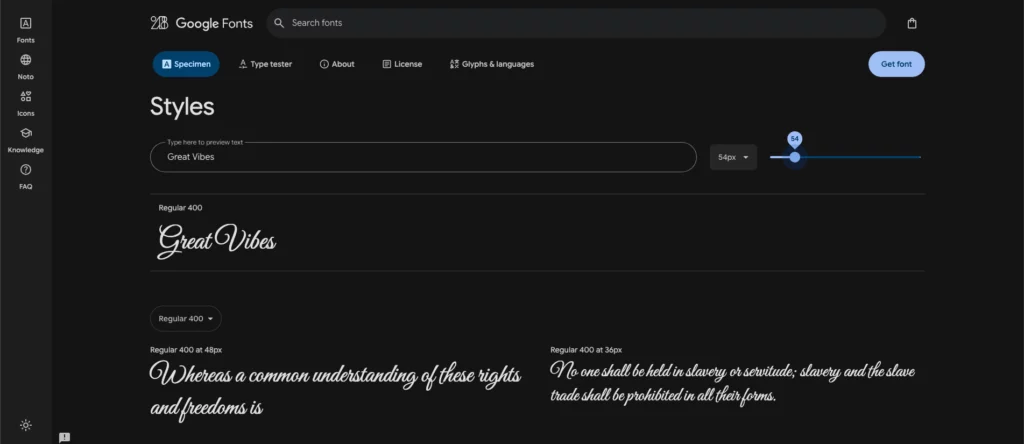
การเลือกฟอนต์ที่เหมาะสมเปรียบเสมือนการเลือกเสื้อผ้าให้กับข้อความของคุณ ในโลกของการออกแบบดิจิทัลที่มีการแข่งขันสูง ฟอนต์มีความสำคัญมากกว่าที่คุณคิด มันไม่เพียงแต่ช่วยให้ข้อความอ่านง่ายขึ้น แต่ยังช่วยสร้างความประทับใจแรกและส่งเสริมตัวตนของแบรนด์ คุณเคยสังเกตไหมว่า แบรนด์ชั้นนำระดับโลกต่างใช้ฟอนต์เฉพาะที่ทำให้เรานึกถึงพวกเขาทันทีที่เห็น
บทความนี้จะพาคุณไปรู้จักกับฟอนต์ภาษาอังกฤษที่สวยงาม 20 แบบ ซึ่งคุณสามารถดาวน์โหลดและใช้ได้ฟรีในปี 2025 พร้อมคำแนะนำเกี่ยวกับวิธีเลือกฟอนต์ให้เหมาะกับงานแต่ละประเภท
ทำไมฟอนต์ถึงสำคัญกับงานดีไซน์
ฟอนต์ คือชุดของตัวอักษรที่มีรูปแบบเฉพาะ น้ำหนัก และลักษณะพิเศษที่ออกแบบมาเพื่อใช้งานร่วมกัน ฟอนต์ภาษาอังกฤษที่มีคุณภาพสูงจะมีความสม่ำเสมอในการออกแบบ อ่านง่าย และมีความยืดหยุ่นในการใช้งานหลากหลายรูปแบบ และองค์ประกอบสำคัญของการออกแบบเพราะมีอิทธิพลโดยตรงต่อความรู้สึกของผู้ชม มันสามารถสร้างความน่าเชื่อถือ ความเป็นมืออาชีพ หรือความคิดสร้างสรรค์ได้โดยไม่ต้องใช้คำพูดใด ๆ
ความแตกต่างของฟอนต์ภาษาอังกฤษในแต่ละสไตล์
ฟอนต์ภาษาอังกฤษมีหลายประเภท แต่ละประเภทมีความโดดเด่นแตกต่างกัน
Serif – มีเส้นตกแต่งเล็ก ๆ ที่ปลายของแต่ละตัวอักษร ให้ความรู้สึกเป็นทางการและคลาสสิก เหมาะกับเนื้อหาที่ต้องการความน่าเชื่อถือ
Sans-serif – ไม่มีเส้นตกแต่งที่ปลายตัวอักษร ดูทันสมัยและเรียบง่าย เหมาะกับการอ่านบนหน้าจอดิจิทัล
Display – ออกแบบมาเพื่อดึงดูดความสนใจ มักใช้กับหัวข้อขนาดใหญ่หรือโลโก้
Script – เลียนแบบลายมือเขียน ให้ความรู้สึกเป็นส่วนตัวและมีศิลปะ
Monospace – ตัวอักษรแต่ละตัวมีความกว้างเท่ากัน นิยมใช้ในการเขียนโค้ดหรืองานที่ต้องการความแม่นยำ
บทบาทของฟอนต์ในการสื่อสารแบรนด์และอารมณ์
ฟอนต์เป็นเสมือนน้ำเสียงของแบรนด์ในรูปแบบที่มองเห็นได้ เมื่อคุณเลือกฟอนต์ที่เหมาะสม มันจะช่วยถ่ายทอดบุคลิกของแบรนด์ได้อย่างมีประสิทธิภาพ
ตัวอย่างเช่น ฟอนต์เรียบง่ายแบบ Sans-serif อาจสื่อถึงความทันสมัยและความเป็นมืออาชีพ ขณะที่ฟอนต์แบบ Script อาจให้ความรู้สึกถึงความเป็นศิลปะและความเป็นส่วนตัว
นอกจากนี้ ฟอนต์ยังสามารถกำหนดลำดับความสำคัญของข้อมูล ดึงดูดความสนใจไปยังส่วนสำคัญ และทำให้การสื่อสารมีประสิทธิภาพมากขึ้น
วิธีเลือกฟอนต์ภาษาอังกฤษให้เหมาะกับงานออกแบบ
การเลือกฟอนต์ไม่ใช่แค่เรื่องของความสวยงาม แต่ต้องคำนึงถึงการใช้งานจริงด้วย ไม่ว่าจะเป็นวัตถุประสงค์และกลุ่มเป้าหมาย การคำนึงถึงความสามารถในการอ่าน และตรวจสอบความเข้ากันได้กับแพลตฟอร์มที่ใช้
ฟอนต์สำหรับงานพรีเซนเทชัน
งานพรีเซนเทชันต้องการฟอนต์ที่อ่านง่ายแม้จากระยะไกล ฟอนต์ควรมีความชัดเจนและเรียบง่าย ฟอนต์ประเภท Sans-serif มักเป็นตัวเลือกที่ดีเพราะความสะอาดตาและอ่านง่าย
เคล็ดลับสำคัญคือการใช้ฟอนต์ไม่เกิน 2-3 แบบในงานเดียวกัน โดยแบ่งหน้าที่ชัดเจน เช่น ฟอนต์หนึ่งสำหรับหัวข้อ อีกฟอนต์สำหรับเนื้อหา
ฟอนต์สำหรับงานกราฟิกโซเชียลมีเดีย
โซเชียลมีเดียเต็มไปด้วยข้อมูลมากมาย ดังนั้นฟอนต์ที่ใช้ต้องสามารถดึงดูดความสนใจได้อย่างรวดเร็ว ฟอนต์ประเภท Display หรือฟอนต์ที่มีลักษณะโดดเด่นสามารถช่วยดึงดูดสายตาได้ดี
อย่างไรก็ตาม ความสมดุลเป็นสิ่งสำคัญ ควรผสมผสานระหว่างฟอนต์ที่มีความโดดเด่นกับฟอนต์ที่อ่านง่าย เพื่อให้ข้อความหลักสะดุดตาและเนื้อหารองสามารถอ่านได้อย่างสบาย
ฟอนต์ที่เหมาะกับเว็บไซต์และ UX/UI
สำหรับเว็บไซต์ ความสามารถในการอ่านคือสิ่งสำคัญที่สุด ฟอนต์ควรทำงานได้ดีในหน้าจอทุกขนาดและโหลดอย่างรวดเร็ว โดยเฉพาะฟอนต์แบบ Sans-serif เช่น Roboto, Open Sans หรือ Inter มักเป็นตัวเลือกยอดนิยมสำหรับเนื้อหาเว็บไซต์ เพราะอ่านง่ายบนหน้าจอดิจิทัล เว็บไซต์ส่วนใหญ่ใช้ระบบลำดับชั้นของฟอนต์ โดยมีฟอนต์ที่มีความโดดเด่นสำหรับหัวข้อใหญ่ และฟอนต์ที่อ่านง่ายสำหรับเนื้อหา
รวม 20 ฟอนต์ภาษาอังกฤษสวย ๆ โหลดฟรี ใช้ได้จริงในปี 2025
ต่อไปนี้คือฟอนต์ภาษาอังกฤษฟรี 20 แบบที่คัดสรรมาเป็นพิเศษ แบ่งตามสไตล์การใช้งาน พร้อมคำแนะนำในการนำไปประยุกต์ใช้
ฟอนต์แนวมินิมอล (Minimal Fonts)
1. Inter
ลักษณะเด่น : ออกแบบมาเพื่อการอ่านบนหน้าจอโดยเฉพาะ มีความชัดเจนแม้ในขนาดเล็ก
เหมาะกับ : งานออกแบบ UI/UX เว็บไซต์ แอปพลิเคชัน
2. Archivo
ลักษณะเด่น : เส้นสายเรียบง่าย มีน้ำหนักหลากหลาย สมดุลระหว่างความทันสมัยและการใช้งานได้จริง
เหมาะกับ : งานพิมพ์ โลโก้ หัวข้อ
3. Satoshi
ลักษณะเด่น : ฟอนต์ Sans-serif ที่มีความเรียบแต่มีเอกลักษณ์
เหมาะกับ : แบรนด์ที่ต้องการความทันสมัย งานออกแบบดิจิทัล
4. Public Sans
ลักษณะเด่น : พัฒนาโดยรัฐบาลสหรัฐฯ มีความเรียบง่ายและอ่านง่ายสูง
เหมาะกับ : เว็บไซต์ราชการ งานที่ต้องการความน่าเชื่อถือ
5. Space Grotesk
ลักษณะเด่น : เป็นฟอนต์ทางเลือกที่ผสมผสานความมินิมอลกับความมีเอกลักษณ์
เหมาะกับ : สตาร์ทอัพด้านเทคโนโลยี ผลิตภัณฑ์ที่มีความล้ำสมัย
ฟอนต์แนววินเทจ / คลาสสิก (Vintage & Classic Fonts)
6. Vesper Libre
ลักษณะเด่น : ฟอนต์ Serif ที่ได้รับแรงบันดาลใจจากงานพิมพ์ยุคเก่า มีความสง่างาม
เหมาะกับ : หนังสือ, บทความยาว, แบรนด์หรูหรา
7. Old Standard TT
ลักษณะเด่น : รูปแบบที่เรียบง่ายแต่คลาสสิก เหมาะกับงานที่ต้องการความเป็นทางการ
เหมาะกับ : นามบัตร เอกสารทางการ งานแต่งงาน
8. Playfair Display
ลักษณะเด่น : ฟอนต์ Serif ที่ได้รับแรงบันดาลใจจากยุคทรานซิชั่น ให้ความรู้สึกหรูหรา
เหมาะกับ : หัวข้อในนิตยสาร โลโก้ งานแฟชั่น
ลิงก์ดาวน์โหลด : fonts.google.com/specimen/Playfair+Display
9. Cinzel
ลักษณะเด่น : เวอร์ชันสมัยใหม่ของฟอนต์คลาสสิกที่มีประวัติยาวนาน
เหมาะกับ : งานพิมพ์, หนังสือ, บทความทางวิชาการ
ลิงก์ดาวน์โหลด : https://fonts.google.com/specimen/Cinzel?preview.text=Cinzel
10. Cormorant Garamond
ลักษณะเด่น : ฟอนต์ Display Serif ที่มีความร่วมสมัยแต่แฝงกลิ่นอายของยุควินเทจ
เหมาะกับ : แบรนด์ที่ต้องการภาพลักษณ์คลาสสิกแต่ทันสมัย
ลิงก์ดาวน์โหลด : https://fonts.google.com/specimen/Cormorant+Garamond?preview.text=Cormorant%20Garamond
ฟอนต์แนวโมเดิร์น / เท่ห์ (Modern & Stylish Fonts)
11. Clash Display
ลักษณะเด่น : ฟอนต์ที่ผสมผสานความเป็น Geometric Sans-serif กับลูกเล่นที่ทันสมัย
เหมาะกับ : โปสเตอร์ หัวข้อใหญ่ โซเชียลมีเดีย
ลิงก์ดาวน์โหลด : fontshare.com/fonts/clash-display
12. Cabinet Grotesk
ลักษณะเด่น : มีความเป็นกราฟิกสูง เส้นสายมีเอกลักษณ์เฉพาะตัว
เหมาะกับ : แบรนด์สินค้าวัยรุ่น งานดีไซน์เท่ ๆ
ลิงก์ดาวน์โหลด : fontshare.com/fonts/cabinet-grotesk
13. Neue Machina
ลักษณะเด่น : แรงบันดาลใจจากตัวอักษรแบบเทคโนโลยี มีความเป็นอนาคต
เหมาะกับ : แบรนด์เทคโนโลยี งานอีเวนต์ วิดีโอเกม
ลิงก์ดาวน์โหลด : pangrampangram.com/products/neue-machina
14. Mondwest
ลักษณะเด่น : ฟอนต์ที่มีความแปลกตาและทดลอง แต่ยังคงอ่านง่าย
เหมาะกับ : โปรเจกต์ที่ต้องการความแตกต่าง งานศิลปะ
ลิงก์ดาวน์โหลด : pangrampangram.com/products/mondwest
15. Poppins
ลักษณะเด่น : ฟอนต์ Variable ที่มีความยืดหยุ่นสูง มีน้ำหนักหลากหลาย
เหมาะกับ : งานออกแบบที่ต้องการความหลากหลายในฟอนต์เดียว
ลิงก์ดาวน์โหลด : https://fonts.google.com/specimen/Poppins?preview.text=Poppins
ฟอนต์แนวลายมือ / ศิลป์ (Handwriting & Artistic Fonts)
16. Reenie Beanie
ลักษณะเด่น : ฟอนต์ลายมือแบบสบาย ๆ ให้ความรู้สึกเป็นกันเอง
เหมาะกับ : บล็อก คอนเทนต์ส่วนตัว การ์ดต่าง ๆ
ลิงก์ดาวน์โหลด : fonts.google.com/specimen/Reenie+Beanie
17. Brygada 1918
ลักษณะเด่น : ฟอนต์ Serif ที่มีลักษณะแบบลายมือ แต่ยังคงความเป็นทางการ
เหมาะกับ : บทกวี หนังสือ อ้างอิง
ลิงก์ดาวน์โหลด : fonts.google.com/specimen/Brygada+1918
18. Satisfy
ลักษณะเด่น : ฟอนต์ Script ที่มีความพลิ้วไหว แต่ยังอ่านง่าย
เหมาะกับ : แบรนด์ความงาม งานแต่งงาน ร้านอาหาร
ลิงก์ดาวน์โหลด : https://fonts.google.com/specimen/Satisfy?preview.text=Satisfy
19. Great Vibes
ลักษณะเด่น : ฟอนต์ที่ผสมผสานความเป็น Script กับความร่วมสมัย
เหมาะกับ : งานแบรนด์สินค้าแฟชั่น บรรจุภัณฑ์
ลิงก์ดาวน์โหลด : https://fonts.google.com/specimen/Great+Vibes?preview.text=Great%20Vibes
20. Pacifico
ลักษณะเด่น : ฟอนต์ Serif ที่มีความเป็นศิลปะและมีเอกลักษณ์
เหมาะกับ : งานศิลปะ โปสเตอร์ นิทรรศการ
ลิงก์ดาวน์โหลด : https://fonts.google.com/specimen/Pacifico?preview.text=Pacifico
ข้อควรระวังก่อนใช้งานฟอนต์ที่ดาวน์โหลดฟรี
แม้ว่าฟอนต์ฟรีจะเข้าถึงได้ง่าย แต่มีบางสิ่งที่คุณควรรู้ก่อนนำไปใช้ในโปรเจกต์ของคุณ
การตรวจสอบสิทธิ์ใช้งาน (License)
ฟอนต์ฟรีแต่ละตัวมักมาพร้อมกับข้อตกลงการใช้งานที่แตกต่างกัน มีการอนุญาตการใช้งานหลายประเภท
Personal Use Only – ใช้ได้เฉพาะงานส่วนตัว ไม่สามารถใช้ในงานเชิงพาณิชย์
Free for Commercial Use – สามารถใช้ได้ทั้งงานส่วนตัวและงานเชิงพาณิชย์
Shareware – ทดลองใช้ฟรี แต่ต้องซื้อสิทธิ์หากต้องการใช้เต็มรูปแบบ
Open Source – ใช้ได้อย่างอิสระ บางครั้งต้องอ้างอิงที่มา
ควรอ่านข้อตกลงการใช้งานให้ละเอียดก่อนนำฟอนต์ไปใช้ โดยเฉพาะอย่างยิ่งในงานเชิงพาณิชย์
ความเข้ากันได้กับภาษาไทยและการแสดงผล
ฟอนต์ภาษาอังกฤษบางตัวอาจไม่รองรับการแสดงผลภาษาไทย หรือแสดงผลภาษาไทยได้ไม่สมบูรณ์ ควรทดสอบการใช้งานร่วมกับภาษาไทยก่อนนำไปใช้จริง
ทางแก้ไขคือการใช้ฟอนต์ภาษาอังกฤษคู่กับฟอนต์ภาษาไทยที่มีลักษณะใกล้เคียงกัน โดยกำหนด CSS font-family ให้เรียกใช้ฟอนต์ภาษาอังกฤษก่อน แล้วค่อยมาใช้ฟอนต์ภาษาไทยเป็นตัวสำรอง
แหล่งรวมฟอนต์ฟรีคุณภาพดีเพิ่มเติม
นอกจาก 20 ฟอนต์ที่แนะนำไปแล้ว ยังมีแหล่งรวมฟอนต์ฟรีคุณภาพดีอีกมากมาย
เว็บไซต์แนะนำสำหรับดาวน์โหลดฟอนต์ภาษาอังกฤษ
Google Fonts – แหล่งรวมฟอนต์ฟรีที่ใหญ่ที่สุด รองรับการใช้งานบนเว็บไซต์ได้ง่าย
FontShare – ฟอนต์คุณภาพสูงที่สามารถใช้ได้ฟรีทั้งงานส่วนตัวและเชิงพาณิชย์
Font Squirrel – มีฟอนต์ฟรีมากมายที่ผ่านการคัดกรองเพื่อการใช้งานเชิงพาณิชย์
DaFont – มีฟอนต์หลากหลายรูปแบบ แต่ควรตรวจสอบสิทธิ์การใช้งานให้ดี
1001 Fonts – มีฟอนต์จำนวนมาก แบ่งหมวดหมู่ชัดเจน ง่ายต่อการค้นหา
เครื่องมือพรีวิวฟอนต์ก่อนดาวน์โหลด
การทดลองใช้ฟอนต์ก่อนดาวน์โหลดเป็นวิธีที่ดีในการประหยัดเวลา นี่คือเครื่องมือที่แนะนำ
สรุป
ฟอนต์ไม่ใช่แค่ตัวอักษร แต่คือเสียงของแบรนด์ เป็นหนึ่งในเครื่องมือที่ช่วยสร้างภาพจำ และความประทับใจแรกเห็น การเลือกฟอนต์ให้เหมาะกับบริบทและกลุ่มเป้าหมายจึงเป็นเรื่องที่ควรให้ความใส่ใจ เพราะมันมีผลต่อความรู้สึก การรับรู้ และการสื่อสารของงานออกแบบทุกชิ้นอย่างแท้จริง